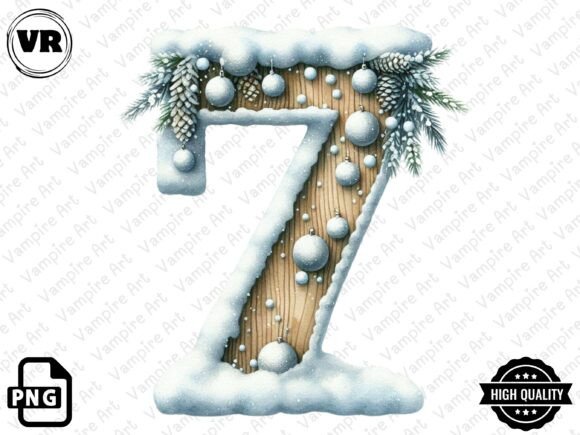
Holiday Typeface and Number Clipart PNG
Encontrar los elementos de diseño adecuados puede ser un desafío, pero Holiday Typeface and Number Clipart PNG ofrece una colección excepcional que eleva tu trabajo al instante.
Elaborado con precisión, Holiday Typeface and Number Clipart PNG proporciona vectores limpios, tipografía suave y una licencia comercial para tu tranquilidad.